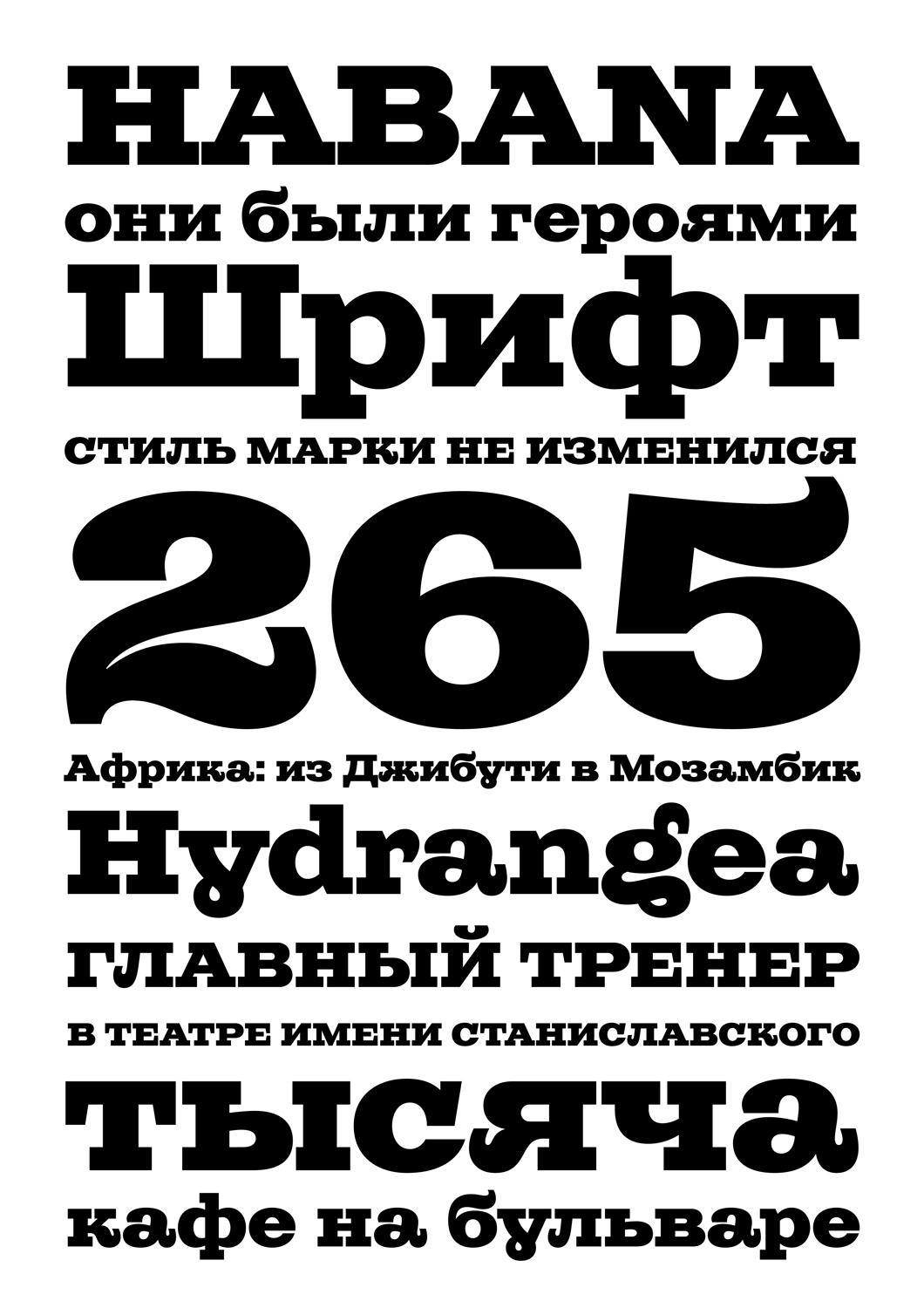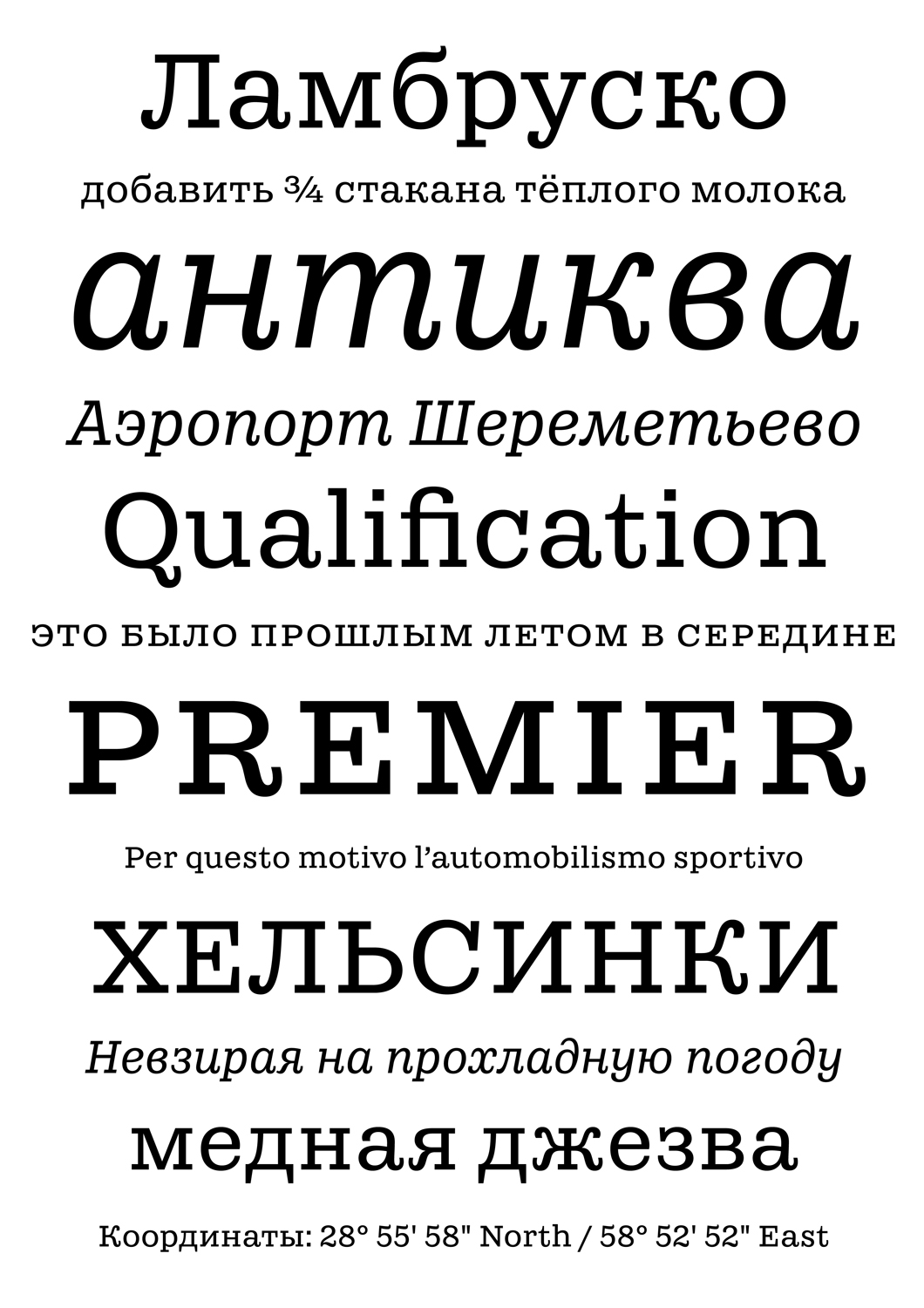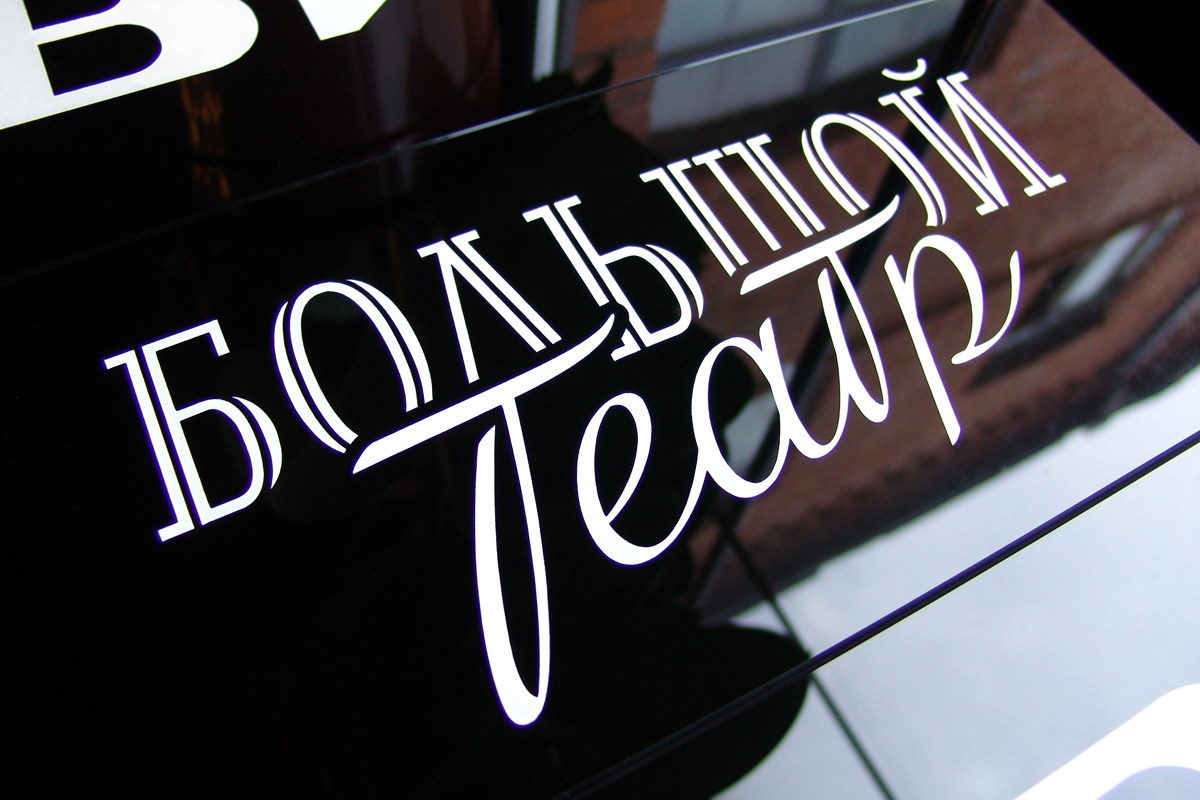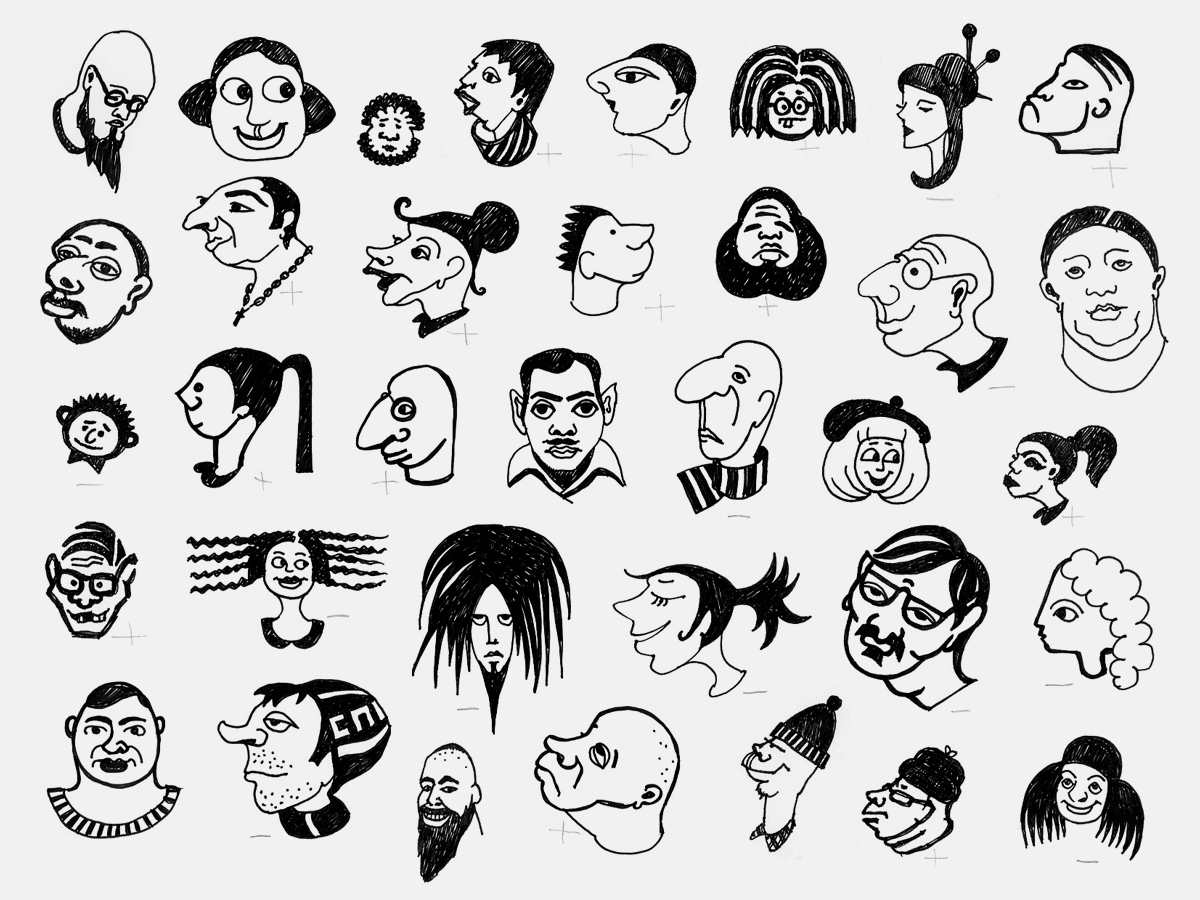
Интервью с Яной Кутьиной и Андреем Белоноговым
Яна Кутьина
Андрей Белоногов
Яна Кутьи­на
Ан­дрей Бе­ло­но­гов
на Кутьина и Андрей Белоногов — графические дизайнеры, художники шрифта и герои того фронта, на котором создаётся графическая культура нашего времени. Два года подряд они участвуют и побеждают в международных конкурсах шрифтового дизайна: сначала это был «Граншан» с дипломами в номинациях «текстовый» и «акцидентный шрифт», 2014-й принёс победу на «Современной кириллице» (шрифты Napoleon и Chetwerg) и приз имени Эмиля Якупова от компании «ПараТайп». Но мы собрались поговорить с Яной и Андреем не о конкурсах и победах, а об их ремесле, совместной работе, любимых дизайнерах, ежедневной практике и вдохновении.
Как настроение?
Рабочее (смеются). Два интенсивных дня на «Серебре набора» немного отвлекли нас от текущих задач, так что мы парой слов между собой перекинулись — и снова нырнули в будни.
Что для вас значит победа на «Современной кириллице»?
Любая победа — это, конечно, приятно, что уж говорить. Ещё, наверное, это лишний повод думать, что мы движемся в верном направлении.
Не могу не спросить: как это вы работаете вдвоём? Как принимаете решения, когда под вопросом ни много ни мало судьба контура, засечки или длина выносных элементов?
Яна: Как? Дерёмся!
Андрей: Если серьёзно, то, к счастью, по принципиальным вопросам у нас мнения сходные.
Яна: Если вдруг и возникают локальные расхождения, то нам несложно договориться — тут кто кого убедит.
На сегодняшний день среди ваших задач больше макетной работы или околошрифтовой?
Примерно пятьдесят на пятьдесят, наверное. В последнее время работы, связанной со шрифтом, стало побольше, и это радует.
В какой момент жизни появился интерес к профессии дизайнера шрифта?
Яна: Интерес зародился ещё в Строгановке. Гля­дя на кар­тин­ки в книж­ках по гра­фи­че­ско­му ди­зай­ну, мы все­гда об­ра­ща­ли вни­ма­ние на шрифт и придавали ему существенное значение. В какой-то момент мы узнали о существовании студии Леттерхед, которая в своих работах использует свои же шрифты. Это впечатлило.
Андрей: Нам захотелось иметь какие-то образцы. Мы набрались наглости и позвонили. Трубку взял, как потом оказалось, Валерий Голыженков, который дружелюбно предложил приехать в студию. Мы встретились, отлично побеседовали, и показалось, что чем-то подобным хотелось бы заниматься и нам.
Кто ещё вас вдохновляет в работе? Вы следите за студиями или самостоятельными дизайнерами?
Яна: Больше всего вдохновляют увлечённые люди, способные поделиться с тобой положительным зарядом. Конечно, мы смотрим вокруг. Нам нравится, что делают Крис Соуэрсби, Сайрус Хайсмит.
Андрей: Часто вдохновляют какие-то конкретные работы, а не творчество в целом. Вот, скажем, шрифт El Grande Джима Паркинсона, или замечательный трафарет Puncho Фреда Смейерса, или Mr. Porter Underware. А Флейшман! Это вообще что-то запредельное.
Яна: Очень классные штуки у Рене Книпа, нравится его проект Arktype с Яно Ханом — весьма самобытно.
Ваши шрифты Astera, Brusque, Cliche, FastFingers, Lustre, Vataga, на­хо­дящиеся сегодня в биб­лио­те­ке «Па­ра­Тай­па», и другие на­ри­со­ва­ны с до­лей юмо­ра. Рас­ска­жи­те по­дроб­нее о за­мыс­ле не­ал­фа­вит­ных про­ек­тов. Есть ли у вас при­ме­ры их ис­поль­зо­ва­ния в жиз­ни?
Мы пытались рисовать шрифты, но понимали, что знаний недостаточно. А вот неалфавитные шрифты — вроде и шрифты, и не требуют чего-то специального. House Industries и Emigre выпускали неалфавитные шрифты, и нам это было интересно. Наверное, в нашем случае дингбаты — это такой мостик, путь к алфавитным шрифтам. Хотя и сейчас мы не потеряли интерес к ним и с удовольствием рисовали бы какие-то картинки, но уже в виде части шрифта или кассы.
Примеров использования мы не видели, но, судя по ежегодным отчётам «ПараТайпа», кому-то они изредка бывают нужны.
В 2011 году вы начали учиться на курсе «Шрифт и типографика» в Британской школе дизайна и закончили его в 2013-м, успешно защитившись с проектами Napoleon (Яна) и Chetwerg (Андрей). Почему вы решили пойти на курс? Ведь вы и до этого создавали шрифты, побеждали в различных конкурсах?
Яна: Когда на «Составе» появились очерки Ильи Рудермана о его учёбе в Гааге, это всколыхнуло наш интерес к шрифту. После возвращения из Голландии Илья организовал курс «Шрифт и типографика» в Британке. Мы какое-то время издалека наблюдали. В это время мы работали, находясь в свободном плавании, течение становилось довольно монотонным и предсказуемым, и нам захотелось чего-то другого — нового, интересного.
Андрей: Да, время от времени мы рисовали какие-то буквы (стоит заметить, что всё это было на очень любительском уровне) и примерно за год до поступления на курс мы даже купили «Фонтлаб». Открыли его пару раз и закрыли. На презентации курса в Британке мы случайно встретили Владимира Ефимова и спросили его, стоит ли идти на курс. Он по своей тактичности не стал советовать ничего конкретного, сказал, что всему можно научиться самому, но это потребует гораздо больше времени и сил. Короче, мы пошли учиться. И, надо сказать, рады, что всё так произошло, и очень признательны Илье.
Что, по-вашему, за годы обучения в Британке было самым важным?
Яна: Самое важное... наверное, то, что Илья старается привлекать на курс все заметные в профессиональной среде фигуры. Было забавно наблюдать, как однажды после лекции Шторма в Чешском культурном центре он на глазах у всех присутствующих за пару минут договорился с Франтишеком (у которого, кажется, были совсем другие планы) о его визите на курс.
Андрей: Постоянное присутствие Тарбеева на курсе — бесценно.
Я помню, что вы поступили на курс с твёрдым намерением создать текстовые шрифты.
Ну да, собственно, на одном из первых занятий мы так и ответили на вопрос Валерия Голыженкова к студентам: «Зачем вы пришли учиться?»
Шрифты Chetwerg и Napoleon в этом году были отмечены жюри конкурса «Современная кириллица 2014». Насколько они изменились со времени защиты на курсе в Британке? В каком направлении вы дорабатывали эти проекты?
Андрей: Сразу после защиты, после периода, когда ты видишь свой шрифт ежедневно, куда больше, чем тебе этого хотелось бы, — совсем не было желания открывать файлы, не то что продолжать работу. Правда, спустя некоторое время Chetwerg открыть-таки пришлось, и даже пришлось его экстренно доделывать — к нам обратился Анатолий Гусев, возникла перспектива увидеть шрифт в работе, а для нас это было интересно и очень важно. В общем, как оказалось, это был нужный стимул для доработки. Конечно, в момент приложения больших усилий его сложно оценить, но когда в будущем шрифт требуется снова и ты вспоминаешь те адские неделю-две, то думаешь: как же замечательно, что был совершён этот рывок. После первого применения тоже нашлось что поправить, так что работа продолжается.
Яна: Что касается Наполеона, то работа тоже идёт: довольно прилично расширился состав знаков, добавилась капитель. Плюс к этому пересмотрена итоговая линейка начертаний. Практически заново начато жирное, и, возможно, появится светлое начертание, которого не было до этого.
Яна, Napoleon ведь развивался «от обратного» — от сверхжирного акцидентного начертания к текстовым. Как ты смогла в текстовых начертаниях сохранить родственную связь с выразительным и пластичным Napoleon Display?
Как не потерять родство — это вопрос, который волновал меня постоянно во время работы. Я переживала, остаётся ли что-то общее между ними, если я последовательно избавляюсь от ряда, как мне казалось, характерных деталей... Поскольку я относительно долгое время пристально смотрела на шрифт с близкого расстояния, в какой-то момент мне вообще стало казаться, что их ничего не роднит (смеётся). Мне нужно было некоторое время не открывать шрифт, чтобы позже, открыв, обнаружить очевидное.
Андрей: Кстати, Шварц, рассматривая шрифт на мастер-классе, отметил, что Яна настолько, насколько было необходимо, избавилась от всего лишнего в текстовой версии, при этом абсолютно сохранив родственную связь с дисплейным начертанием.
Как создавался Napoleon Display?
Яна: Он вырос из довольно диких зарисовок. Часть безумных знаков не выжила, но есть несколько, которые остались практически такими, какими были нарисованы изначально. С другими из-за коротких выносных элементов пришлось повозиться уже в процессе — это было интересно, хотя сказать, что до начала работы я испытывала какие-то особые чувства к этому типу шрифтов, не могу.
C какими малоконтрастными кларендонами ты сверялась, работая над текстовыми версиями Наполеона?
Я поглядывала на брусковые шрифты: Guardian и Stag, Centro Slab, на Eames. Но всё же моей отправной точкой было акцидентное начертание, которое в основном и направляло работу. Вообще, для моментов, когда возникают какие-то вопросы или сомнения, у нас с Андреем есть такая поговорка: «Посмотри, как у других ребят». При этом «другими ребятами» могут быть как сверстники, так и Мэтью Картер, условно говоря. Но часто, вроде бы сверившись, делаешь вывод, что те или иные вопросы все решают по-разному и в твоём конкретном случае решать тебе.
Андрей, какие задачи ты перед собой ставил, разрабатывая Chetwerg?
Я задумал сделать условно нейтральный текстовый шрифт с широким диапазоном применения. Ориентировался на собственный вкус и старался сделать хорошо, в меру своего понимания. Размышляя над количеством начертаний, решил ограничиться минимумом: нормальное, курсивное, жирное. При этом хотелось сделать полноценный инструмент — с капителью, несколькими сетами цифр, лигатурами в латинице и т.п. Уже после мне задавали вопрос: а где жирный курсив? Но я по-прежнему считаю, что в нём нет нужды при работе с текстом, поскольку курсив и жирное начертание дают два различных уровня выделения в тексте, и этого, в общем-то, достаточно. Правда, есть у меня мысль дополнить шрифт ещё одним начертанием, но это пока на уровне идеи...
Chetwerg — компактная шрифтовая семья из трёх представителей, предназначенная для ши­ро­ко­го при­ме­не­ния. Со­дер­жит ка­пи­тель, несколько видов цифр (маюскульные и ми­ну­скуль­ные, пропорциональные и табличные, капи­тель­ные, индексы), на­бор латинских ли­га­тур. Chetwerg поз­во­ля­ет на­би­рать тек­сты на боль­шин­стве язы­ков, ис­поль­зу­ю­щих ки­рил­ли­че­ский ал­фа­вит, и на основ­ных ев­ро­пей­ских язы­ках.
Ты против избыточности при проектировании шрифтов?
Это осознанная позиция именно для данного проекта. Но, если вдумчивому дизайнеру под конкретную задачу потребуется, например, Chetwerg Medium или Semibold, есть возможность их интерполировать.
Четверг вызывает у меня ассоциации со многими шрифтами Герарда Унгера и Картера. На какие проекты ты ориентировался?
В самом начале, на стадии замысла, у меня было приблизительное представление, что образ будущего шрифта находится где-то между Таймсом и Школьной. Конечно же, я смотрел на Джорджию. То, что это объективно хороший шрифт, сомнений нет, но он (как и Чартер, кстати) очень близок мне и по субъективным ощущениям. Tiempos, Mercury, Fleischmann, Lyon, Arnhem — каждый из этих шрифтов в какой-то степени служил ориентиром, но основной упор я делал на кириллицу, а её в этих шрифтах нет.
Какие критерии качества текстового шрифта вы для себя выработали? Как тестируете и проверяете шрифты?
Равномерность набора, наверное, самое основное... Мы не вырабатывали каких-либо критериев, по крайней мере вслух друг другу их не проговаривали. Часто всё происходит просто на уровне «нравится — не нравится», «хорошо — плохо».
Тестируем самым обычным способом, как делают все: распечатываем тексты и проверяем, вносим правки, распечатываем и проверяем...
Что ближе вам — техническое совершенство и невидимая типографика или эмоция, «вкус чтения» по Юрию Гордону?
На данном этапе для нас, наверное, важнее всё-таки первое. Но надо ли противопоставлять? Странно, если шрифт для чтения будет неудобочитаемым при своей эмоциональности. Хотя всему своё место, если есть специфическая задача сделать эмоциональный, «вибрирующий» шрифт — почему нет? Мы и с Зузаной Личко готовы согласиться: лучше читаешь то, что читаешь чаще.
Во многом ваш стиль узнаваем по леттерингу для различных журналов, издательств и дизайн-студий. Пересекается ли работа в этом жанре с разработкой шрифта? Могут ли, например, какие-то идеи в процессе создания надписи перекочевать в полноценный шрифт?
Яна: Леттеринг — это вещь в себе, со своим внутренним ритмом, акцентами, рифмами. К нему более применимы эффектные ходы, которые могут, например, ярче окрасить смысл написанного. И потом, леттеринг — всегда конкретное слово, фраза, определённое сочетание букв, заданное местоположение, а со шрифтом никогда не знаешь, что и где им будет написано. Могут ли быть пересечения? Пока что, пожалуй, их не было, но исключать такую возможность не стоит.
Андрей: Ко шрифту совсем другой подход, более основательный. От общего к частному, к деталям, и снова к общему... Скорее обратное возможно: например, мы использовали наши трафаретные шрифты как основу для создания надписей для пары обложек. Бывает, в ход идут какие-то наработки, шрифтовые эскизы.
Если внимательно посмотреть на ваши работы в жанре леттеринга, то можно заметить в буквах много отсылок к советской типографике — рисованным книжным титулам, вывескам, мелкой полиграфии вроде авиабилетов или бирок. Чем вас вдохновляет стилистика советской эпохи?
Андрей: Сложно сказать... Видимо, непосредственностью, самобытностью, иногда наивностью или, напротив, профессионализмом. Есть в ней что-то такое, чего сейчас нет... чего сегодня не хватает. А потом, это наши буквы, не всё же латиницей вдохновляться. Это кладезь, и, если покопаться, можно многое найти, пока ещё можно.
Как вы добиваетесь того, что подобная стилистика органично встраивается в задачи ваших заказчиков?
Яна: Конечно же, мы не пытаемся встраивать советскую стилистику в любой заказ. Обращение к ней всегда осознанное в соответствии с задачей, а иногда это пожелание заказчика. Если есть замысел использовать этот стиль, то мы формируем некий собирательный образ, который, на наш взгляд, хорошо подходит для конкретной ситуации.
Довольно необычным по исполнению оказался проект офисной навигации для «Афиши-Рамблер». Как вам работалось на этом поле?
Мы с удовольствием откликнулись, когда арт-директор «Афиши» Даша Яржамбек уже напрямую к нам обратилась с предложением продолжить работу над проектом и сделать порядка тридцати табличек (как ты помнишь, проект начинался как совместный — Британки и издательского дома «Афиша-Рамблер»). У них в офисе довольно оригинальные названия, например, переговорные комнаты названы по станциям кольцевой ветки метро, и часть надписей выполнена нами в этом стиле — именно в стиле, поскольку связи с конкретным написанием станции в жизни нет.
Мы были ограничены только заданным форматом стекла (некоторые названия написаны в двух вариациях размеров и пропорций, поскольку висят дважды — непосредственно в редакциях и отделах и на этаже), а в остальном пользовались предоставленной свободой. В целом опыт оказался необычным и довольно трудоёмким — только работа маркерами на финальном этапе заняла около пяти дней.
Один из недавних проектов — шрифт «Ударник». Для меня это такой собирательный образ городской и промышленной трафаретной типографики, и, что характерно, этот шрифт мало связан со знаменитыми конструктивистскими палочными шрифтами. Или я ошибаюсь? Чем вас так привлекают трафаретные шрифты?
Яна: Мы думали, с чем поучаствовать в «Современной кириллице». Нам казалось, что Наполеон и Четверг могут быть знакомы жюри благодаря их прошлогодней победе на «Граншане», да и подать на рассмотрение ещё никому не известную работу было интересней. Поэтому решили придумать что-то на тему, которая давно занимала нас.
Андрей: До дедлайна оставался месяц, и мы решили, что это вполне может стать стимулом для выполнения проекта в ограниченный срок. Но я хочу ответить на твой вопрос: мы делали именно палочный шрифт 20-х годов.
Я сейчас подумал, что в действительности при существующем мощном собирательном образе палочного конструктивистского шрифта в цифровой форме подобных шрифтов сделано не так много. Да, Тагир Сафаев работал в этой области, Валерий Голыженков сделал много палочных шрифтов...
Андрей: Мне кажется, у Валерия немного другая история — его шрифты без конкретных привязок ко времени. Что же касается всем известного Rodchenko — он очень брутальный, квадратный. И в нём есть знаки, которые сегодня выглядят... непривычно, скажем так, хотя понятно, почему Тагир Сафаев выбрал именно такие формы. И они мгновенно отсылают к той эпохе — посмотри на З, например. Мы же хотели приблизить эту стилистику к нашему времени, выбрать более подходящие для сегодняшнего дня формы, чтобы шрифт можно было использовать не только в стилизации «под двадцатые», но и в повседневности.
Яна: И мы смотрели больше не на работы Родченко, Стенбергов, Клуциса — имена, которые у всех на слуху, а на работы менее известных оформителей (Дмитрия Буланова, например, правда, теперь и он известен благодаря энтузиастам). Потом мы стали думать, как шрифт развить, и попробовали сделать контурное (inline) начертание, характерное для того времени, и, конечно, трафарет, поскольку тогда и он был очень распространён. Его часто использовали в печати, в обложках книг и журналов, поэтому нам показалось, что трафаретные начертания тоже будут уместны.
Каких инструментов вам не хватает для работы?
Сейчас всё более важным становится умение оптимизировать рабочий процесс благодаря программированию. Этим нам предстоит овладеть — знание технологий позволяет часть монотонной работы выводить из ручного режима.
Какие книги стоят на вашей типографической полке?
Весь Кричевский, «Книга про буквы» Ю. Гордона, «Искусство шрифта» в оформлении Жукова, «Великие шрифты» В. Ефимова, Letter Fountain... Книг немало — это те, что вспомнились первыми.
Что вы думаете о современном состоянии шрифтового дизайна как профессии? Есть мнение, что Россия переживает бум шрифтового дизайна.
Да, наверное, это можно назвать бумом. В конце концов, ещё не так давно дизайнеров шрифта можно было пересчитать по пальцам, а теперь их... десятки, видимо. Радостно, что расширяется география — Владивосток, Иркутск, Барнаул, Екатеринбург, Брянск, Петербург... Это очень здорово. Об интересе к шрифту можно судить по географии участников «Серебра набора».
А говоря о состоянии в целом — качеству шрифтов ещё есть куда расти, конечно.
Не собираетесь ли вы выпускать свои шрифты в открытую продажу?
Собираемся. Наверное, надо. Примерно так мы отвечаем уже год-полтора, и даже неловко снова это говорить. На какой-то определённой схеме продажи шрифтов в целом мы пока не остановились. Сейчас нам кажется более комфортной продажа не вообще, а под конкретный проект, задачу.